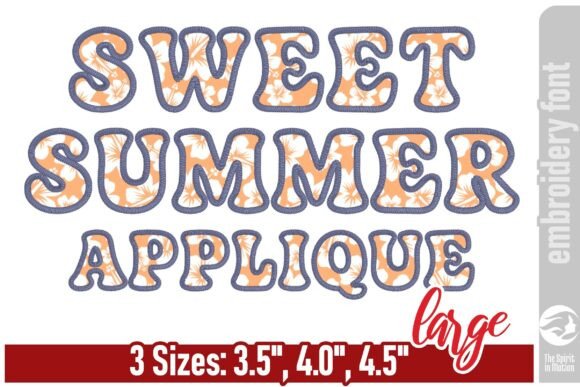
Sweet Summer Groovy Applique Font - L
適切なデザイン要素を見つけるのは難しい場合がありますが、Sweet Summer Groovy Applique Font - Lは作品を即座に引き立てる優れたコレクションを提供します。
POD(オンデマンド印刷)製品、結婚式の招待状、またはソーシャルメディアのグラフィックを作成している場合でも、Sweet Summer Groovy Applique Font - Lは理想的です。